Heute startet das Crowd-Funding für ein ungewöhnliches Filmprojekt: Der junge Designer und Multimedia-Künstler Yanone (siehe auch: Amman – die Stadt, die Schrift, der Film, Fontblog am 19. 10. 2010) dreht einen Tanzmusikfilm, dessen Konzept einer neuen Schriftfamilie Antithesis entlehnt ist. Sie ist Yanones Meisterstück der Schriftgestaltungsklasse Type and Media an der Königlichen Akademie in Den Haag. Ihre Besonderheit: Die Spannung zwischen drei ungleichen Polen. Anders als bei vielen Schriftfamilien üblich, besteht sie nicht aus einer Vielfalt von Schnitten, die dem gleichen Konstruktionsprinzip folgen. Antithesis besteht aus nur drei Schnitten, deren Konstruktion sich innerhalb der Formensprache maßgeblich unterscheidet. Die Normale ist eine scharfkantig geschnittene Slab-Serif, die Kursive eine verbundene Schreibschrift und die Fette eine serifenlose Grotesk — in der Schriftenwelt ist diese Kombination eher selten, wenn nicht sogar einmalig.
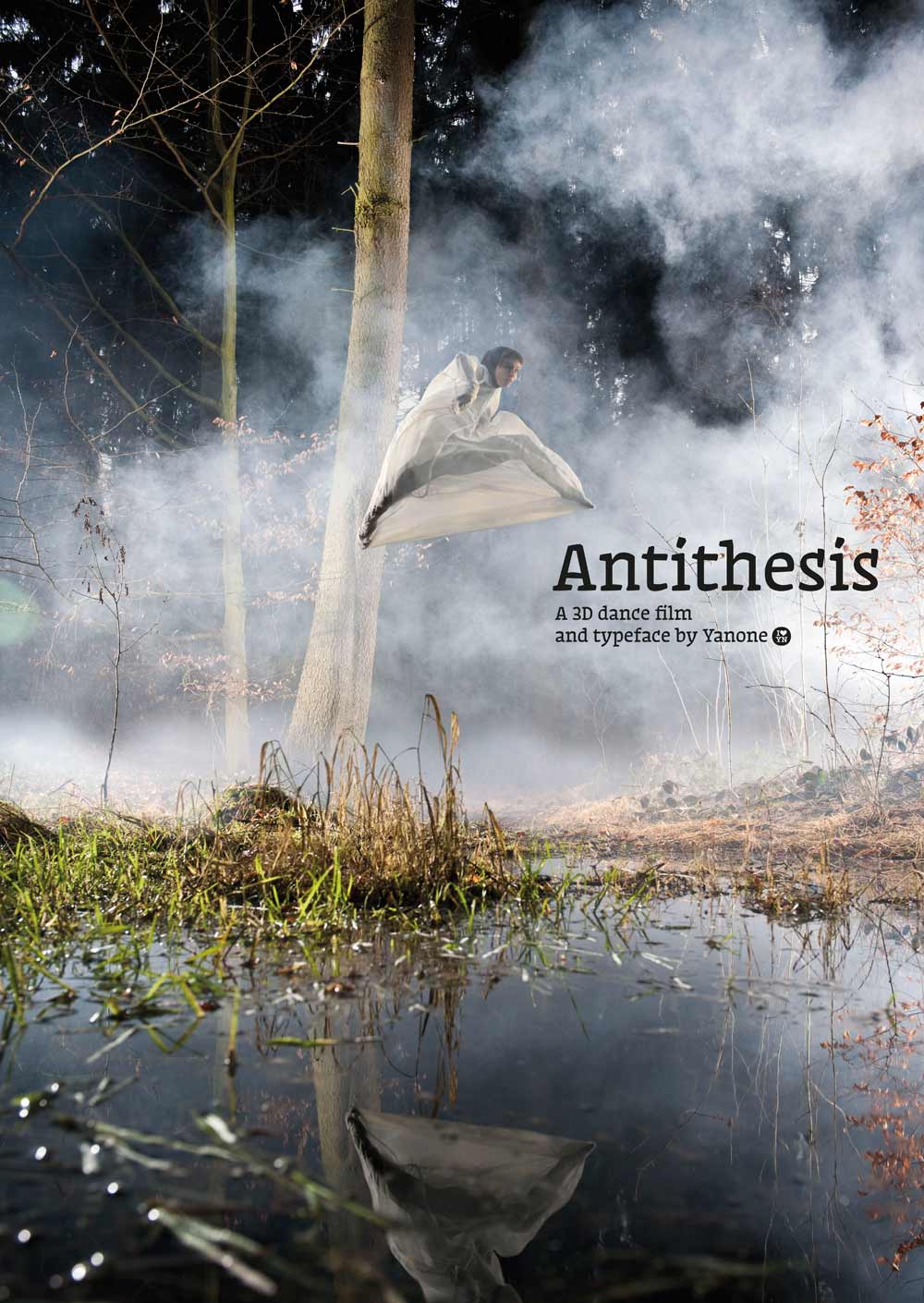
Schon während des Studiums hatte Yanone die Idee, dieses Konzept der Spannung für einen Kunstfilm zu verwenden. Im Sommer 2011, nach Ende des einjährigen Master-Studiums, hatte er nach Gesprächen mit der langjährig befreundeten freien Dresdner Tänzerin Johanna Roggan und mehreren Festivalbesuchen in der Psytrance-Szene die entscheidende Idee: Ein ungefähr zehnminütiger Tanzmusikfilm, in dem er Johanna Roggan ganz ins Rampenlicht stellt und ihr die Freiheit lässt, die gemeinsam erarbeitete Handlung rund um die Spannung zwischen drei Polen, den drei Phasen der philosophischen Dialektik (These, Antithese und Synthese) und den drei Phasen der Entstehung des Universums nach hinduistischem Glauben (Entstehung, Dauer und Auflösung) aufs Parkett zu bringen.
Der Film soll außerdem durch eine aufwendige 3D-Produktion begeistern. »Ich bin beeindruckt vom Medium des 3D-Films«, so der Schriftkünstler und angehende Filmemacher, »aber auch enttäuscht von der geringen Bereitschaft erfolgreicher 3D-Kinofilme, sich über die bloße Räumlichkeit hinaus kreativ mit dem Medium auseinander zu setzen. Schwerter und Bälle, die den Zuschauern ins Gesicht fliegen, können es noch nicht gewesen sein.« Schließlich lag auch der Gedanke nahe, die Filmmusik in die Räumlichkeit zu tragen. Der Berliner Komponist Georg Bauer war begeistert vom Thema und schnell bereit, die Komposition und Produktion der Musik im Raumklang zu übernehmen.
Finanziert werden soll der Film durch das zunehmend erfolgreiche Crowd-Funding, den massenhaft eingeworbenen Spenden von Interessenten aus aller Welt über Internet-Plattformen wie Kickstarter oder Indiegogo. »Ich bin mir bewusst«, sagt Yanone, »dass vor allem bei Kunstfilmen den Filmemachern über Crowd-Funding eingeworbenes Geld nicht gerade geschenkt wird«. Deshalb hat er eine Idee, die ihm Mut macht. Als Gegenleistung möchte er den Spendern neben gedruckten Plakaten die zum Projekt gehörende Schriftfamilie Antithesis in digitaler Form schenken. Eine tolle Gelegenheit für Gestalter mit Interesse an neuen Schriften, die später professionell erscheinende Schriftfamilie zu einem Bruchteil ihres Werts zu ergattern. »Zwar verliere ich durch das Verschenken der Schrift an die Spender viele spätere Käufer, doch immerhin kann ich dadurch die Produktionskosten des Films tragen«, freut sich Yanone.
Im Winter möchte Yanone die Schriftfamilie fertig stellen, damit er sie alsbald an die Spender versenden kann. Im Frühjahr und Sommer 2013 wird er mit seinem Team den Film abdrehen und im Herbst nachbearbeiten. Gegen Ende 2013, also gut ein Jahr nach Beginn der Spendenaktion, soll der Film veröffentlicht werden, im Internet und auf eigens organisierten Vorführungen. Zur gleichen Zeit soll dann die Antithesis-Schriftfamilie exklusiv über das FontShop-Netzwerk vermarktet werden.